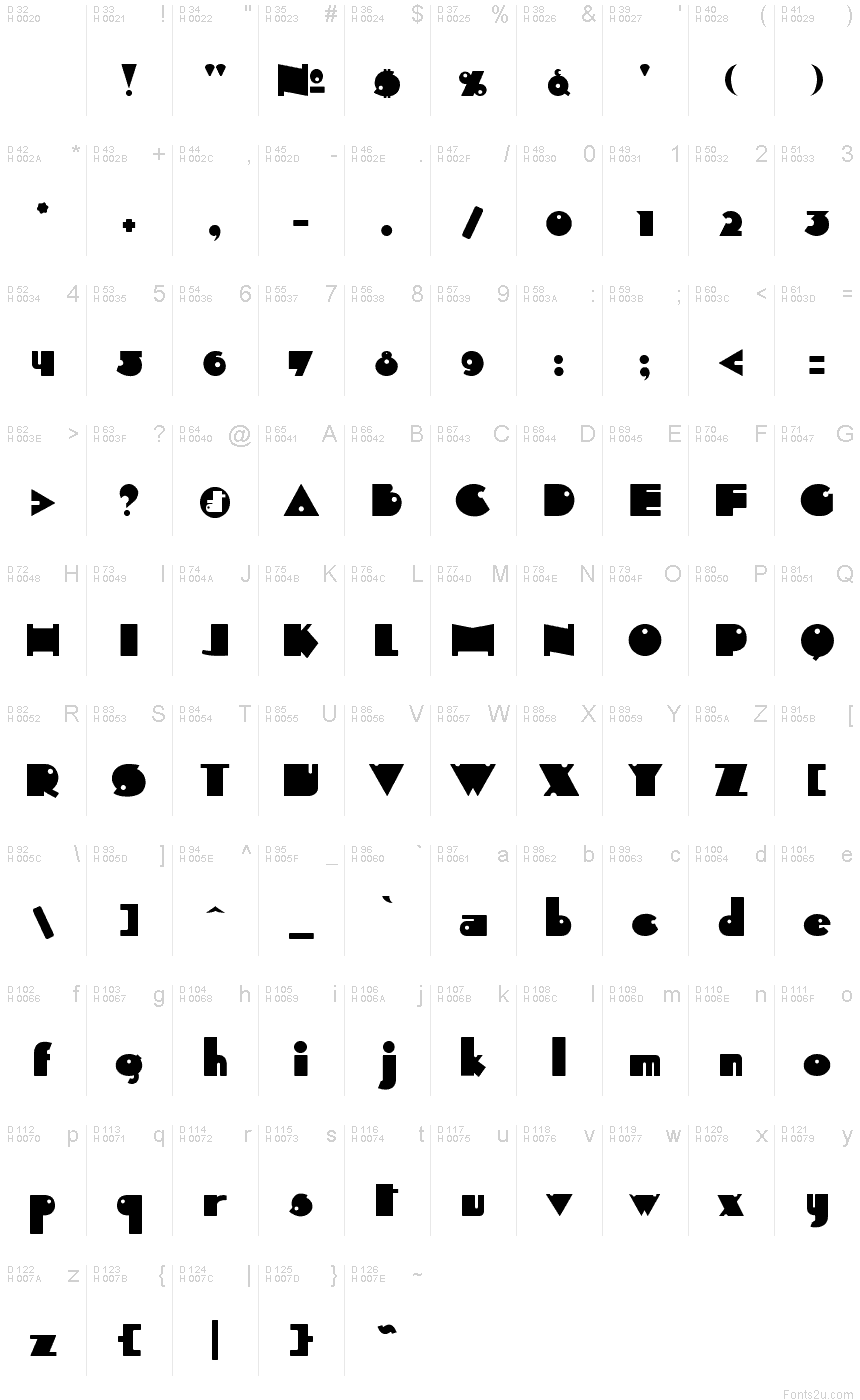
Independant, stworzony przez Phynette & Apostrophic Laboratories, to darmowy, utrzymany w stylu retro krój displayowy, inspirowany europejskimi szyldami z lat 30. Jego ciężkie, wyraziste kształty oraz wydrążone okrągłe detale przypominają litery wycięte z grubego kartonu, nadając każdemu słowu odważny, niemal rzeźbiarski charakter. Zaokrąglone rogi łagodzą tę masę, dzięki czemu font jest bardziej zabawny niż surowy – jakby zabytkowe liternictwo sklepowe zostało powiększone na potrzeby ekranu.
Dzięki Independant zyskujesz wyrazisty, przyciągający wzrok rytm, który świetnie sprawdzi się na plakatach, w logo, na opakowaniach, okładkach albumów, ulotkach i odważnych szyldach. Ten darmowy font najlepiej prezentuje się w dużych rozmiarach, gdzie jego nietypowe formy mogą w pełni wybrzmieć. Połącz go z czystym, lekkim bezszeryfowym krojem pisma w tekstach towarzyszących, aby zachować czytelność i nowoczesny wygląd projektu.